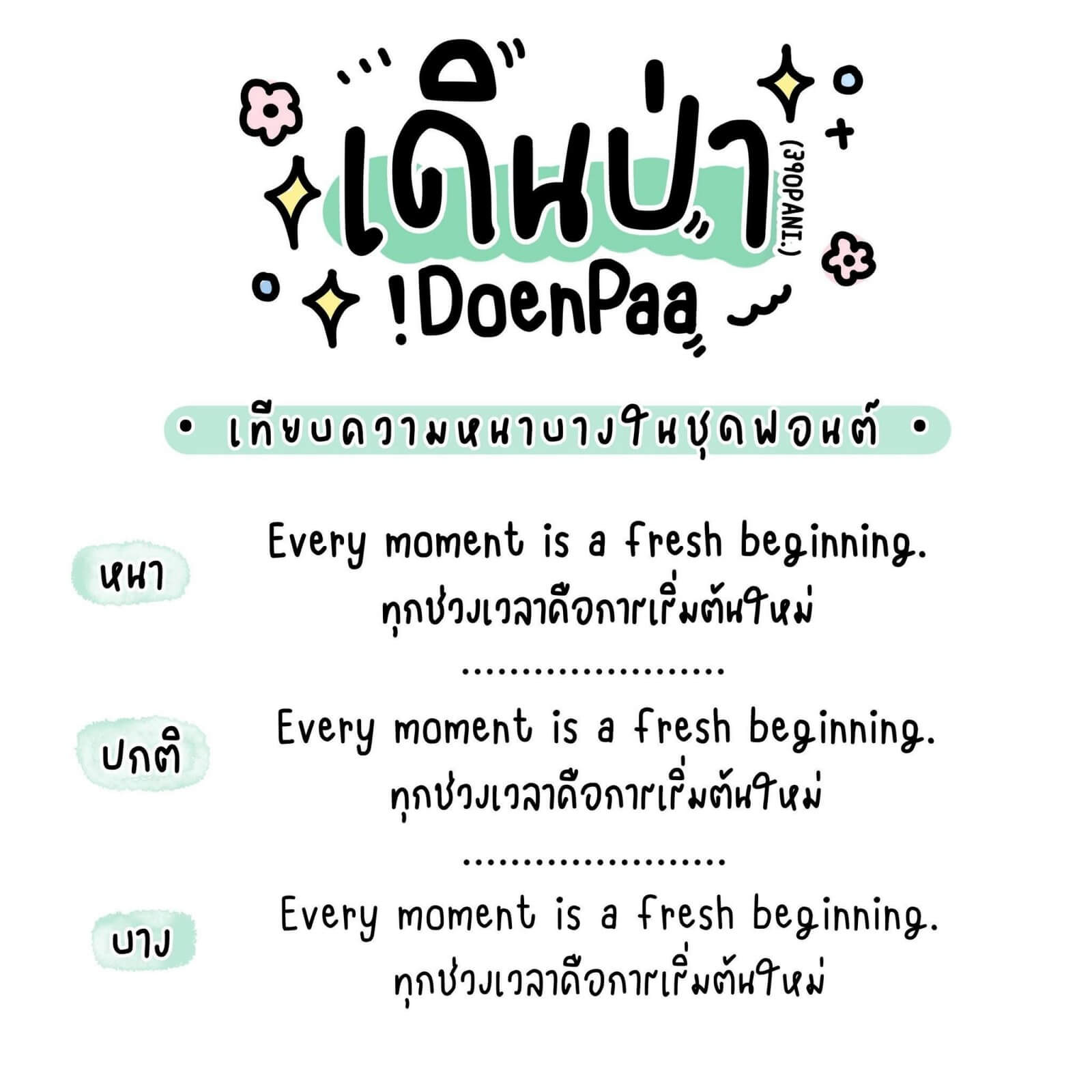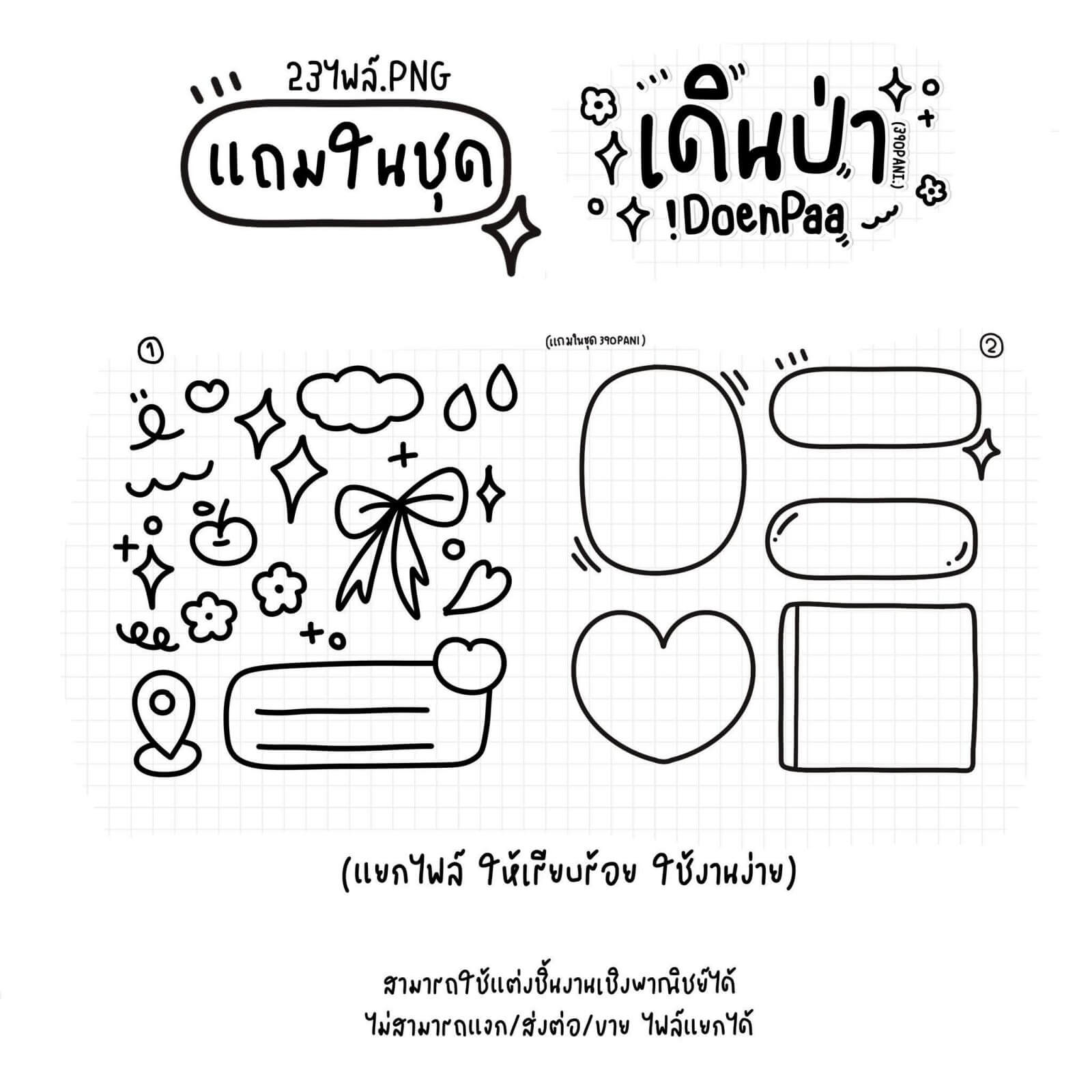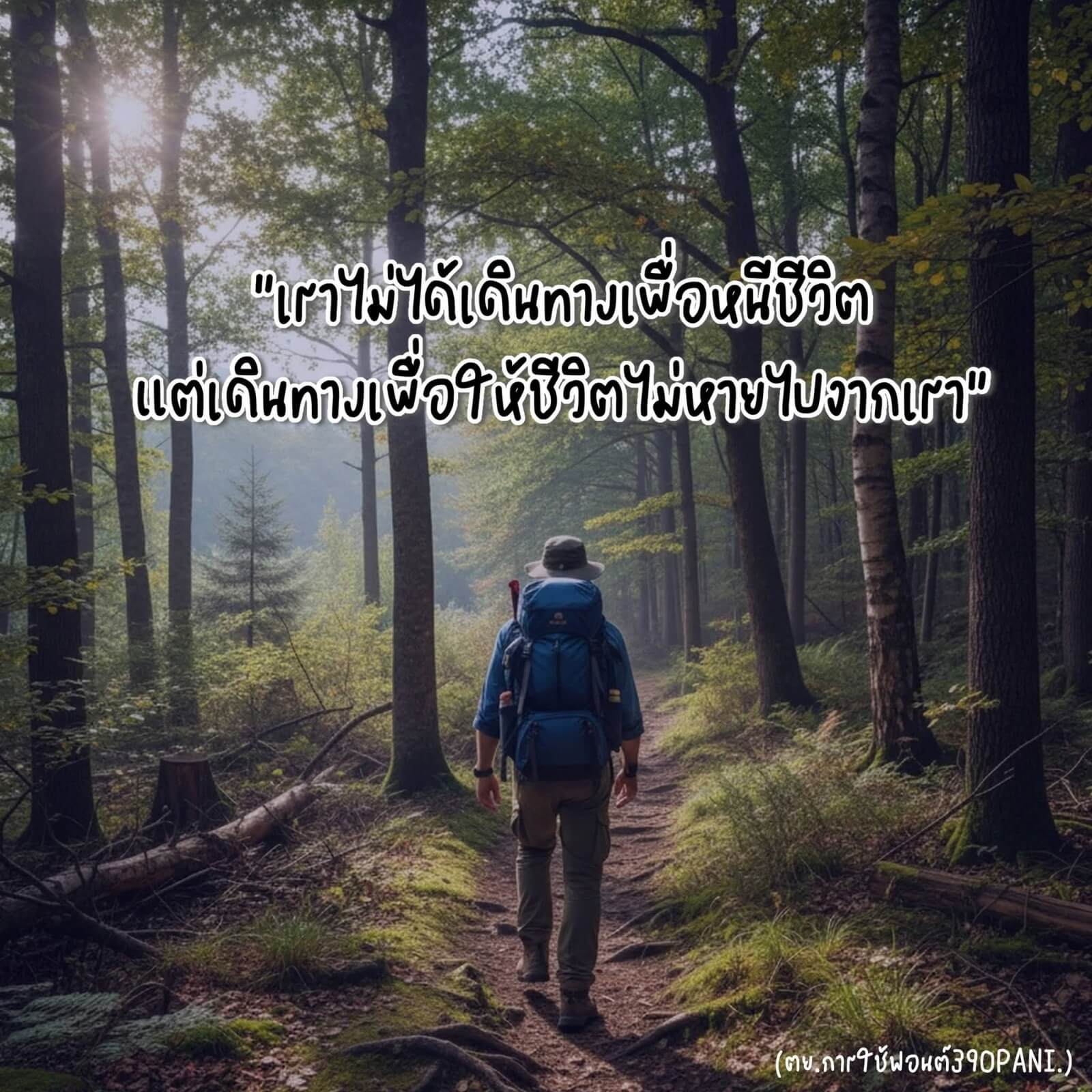
390PANI.เดินป่า
ฟอนต์ 390PANI.เดินป่า – ฟอนต์เป็นตัวหวัดๆ เหมือนเขียนเอง ทำให้ชิ้นงาน ดูชิลๆ เข้าใจง่าย คูลๆ แต่ชิ้นงาน ออกมาได้หลายแบบ (ในชุดแอนวาดของตกแต่งแถมด้วยค่ะ)
– วาดกรอบข้อความ แถมให้อีกชุด